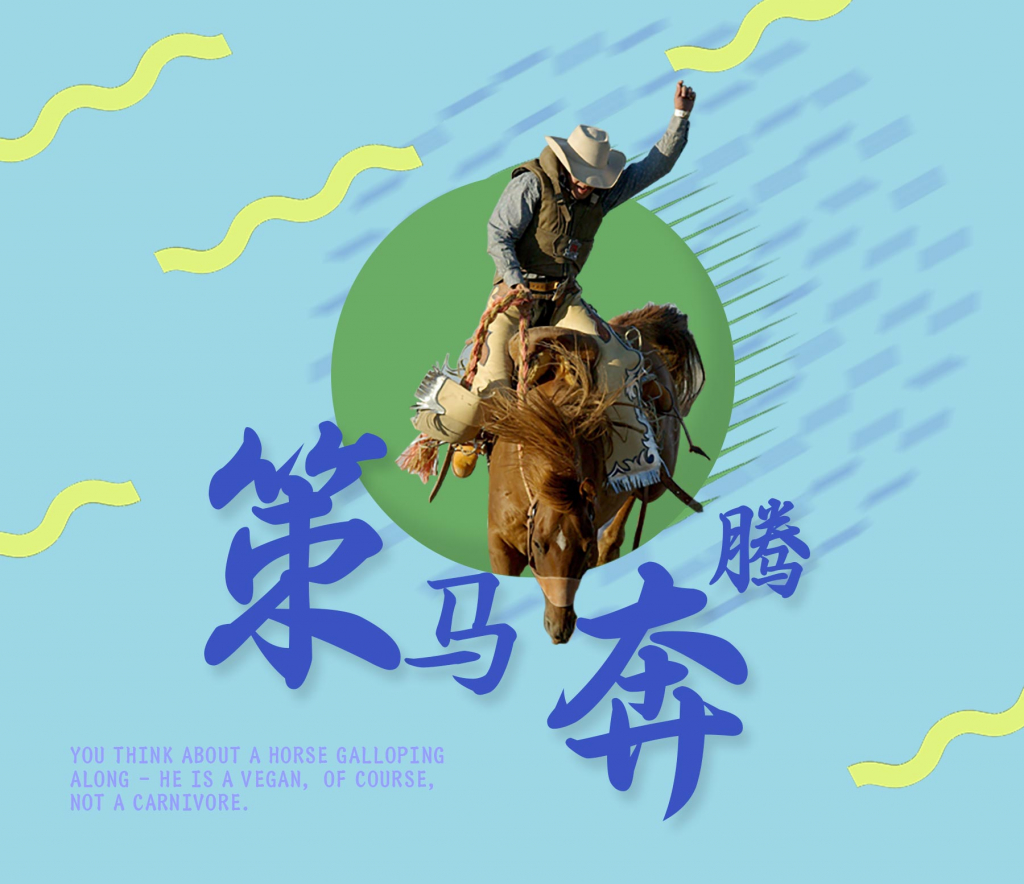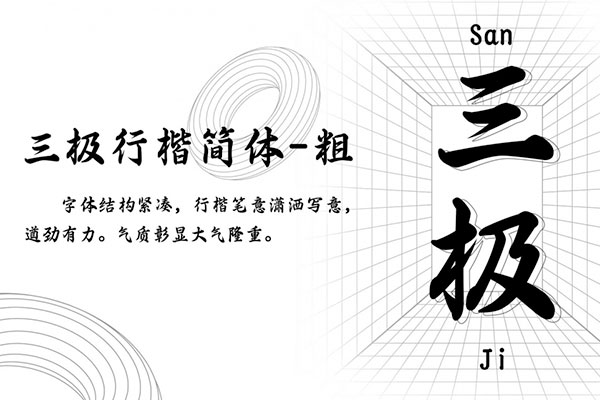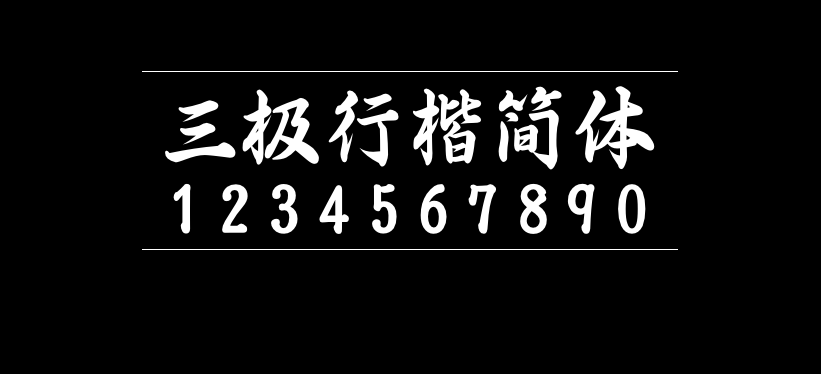
三极行楷简体
三极行楷简体是三极字库推出的免费商用字体,该字体结构紧凑,行楷笔意潇洒写意,遒劲有力。以春联为名,气质彰显大气隆重。本作品适用于印刷媒介的标题及广告语、各类屏幕显示及影视字幕、游戏等。
三极行楷简体适用媒介:杂志、书籍、广告、标志、宣传册、店招、包装、影视、动漫、游戏。
三极行楷简体字符已覆盖GB2312标准的6763字,大家可以放心下载使用!